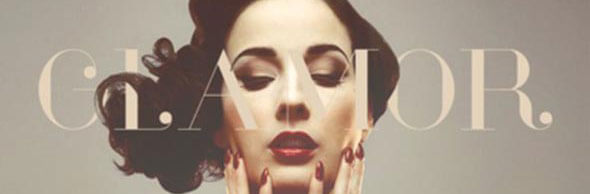
ダウンロード可能な25の大文字フォント
昨今、デジタル世界では字体やデザイン、また、どのように見られるかといったことが注目されています。もし、あなたがウェブデザイナーや電子広告代理店なら、プロジェクトのために、きちんとしたフォントを使うことが重要になります。なぜなら、フォントにはあなたのデザインを目立たせたり、訪問者や顧客を引きつけたりする力があるからです。
字体や書体が仕事の出来に大きな影響を与えることは疑いの余地がありません。デザイナーは、何かを制作する際には、字体のもつさまざまな法則に注意を払う必要があります。たとえば、書体を使う際に重要な法則のひとつは、ウェブサイトで互換性のある2種類のフォントが使用できるということです。3つや4つの書体を超えると、内容から離れ始め、読者が混乱することになり、結果的にサイトから立ち去ってしまうことになってしまいます。
そこで、あなたの仕事をより効率よくするために、ウェブですべて無料でダウンロードできる大文字フォントを探すことにしました。このようにして、あなたを手助けし、応援することのできる25の無料大文字フォントを集めました。これらの素晴らしい大文字フォントのほとんどは、個人用にも商用にも無料でご利用いただけます。私たちとともに、気軽に字体を共有しましょう。
Intro Condensed
この豪華なセットは50の個性的なフォントと太字から作られています。あらゆるサイズの見出しに適しており、どんなタイプの背景にも合います。Tシャツやポスター、ロゴに最適です。掲載元のサイトをご覧になれば、このフォントが洗練されたグラフィックデザインのなかで、どのように使用されているのかといった様々な例をみることができます。
Rex
Rexは3つの太字(light、bold、bold inline)が選択可能なフォントです。すべて大文字のこちらのフォントは、あらゆる種類の背景や、Tシャツ・ポスター・ロゴへのアイデアに適しています。すべて大文字のフォントですが、大文字と小さい大文字の間に違いが見られます。この小さなこだわりが、あなたのプロジェクトに大きく貢献することでしょう。
La Mana
La Mañaはxハイトと、それに適した横幅が特徴のスラブセリフです。美しい先端や素晴らしいマチがあり、見出しや広告に最適です。特別な注意を払って作られており、2種類の太さ(regularとrelief)と175種類のオープンタイプの合字、1000組以上のタイトカーニングはご自身のフォントライブラリを、手動で素晴らしいものへと変えてくれることでしょう。
Uni Sans
Uni SansはFontfabricから提供されています。4種類の大文字の太さが使用されており、無料でダウンロードすることができます。掲載元のリンクでは、どのようにこのフォントを使用するかご覧になることができます。
Langdon
LangdonはXLN Telecomの新しい書体です。しっかりとした力強い書体は、個人用および商用どちらでも利用可能です。イギリスのスティーブン・ボナーとグラフィックデザイナー、イラストレイター、タイポグラファーが共同して作成しました。
Baron
こちらの大文字表記は古典的なサンセリフフォントファミリーをもとに作成されました。ポスターならびに見出しへの使用が理想的です。ユニークな外観はとても目立ちますので、デジタル媒体と印刷媒体の両方へのご利用を強くおすすめします。
Hipstelvetica
Hipstelveticaは有名なヘルベチカデザインに影響を受けて作成されました。こちらの斬新なフォントは個人および商用、どちらも完全に無料です。力強く幾何学的な見た目は、見出しにおすすめです。
Bebas Neue
Bebas Neueは新しく4つの要素(thin、light、book、Regular)を取り込んだ優雅なサンセリフ書体です。こちらの書体はウェブ、印刷、アート、あるいは商用にも適しています。面白いことに、今ではこのフォントは「ヘルベチカの無料のフォント」として知られています。
Code
Codeは先進的で高級な書体です。あらゆる種類のグラフィックデザイナー、その他ポスター、ロゴ、バナーといったアイテムに利用できるでしょう。このフォントはとても多様で、多くの言語でご利用いただけるうえに、MacとPCのどちらにも互換性があります。
Komoda
Komodaは見出しや論評、ポスターデザインに適したサンセリフ書体です。この書体は個人利用及び商用利用どちらも無料です。転載元のリンクでは、このフォントのすべての字体を見ることのできる動画が視聴できます。
Fancy Me
Fancy Meフォントは現代的で論評に最適です。こちらの書体も個人利用、商用利用ともに無料です。とても素晴らしいフォントなので、ダウンロードした後にさらにご利用いただくために、ご自身のフォント目録に追加することをお勧めします。
Canter
Canterはタイトルやポスター、見出しへの表示のために作成された、すべて大文字のフォントです。特に優れた書体は6種類の太文字にあります。アメリカのニューヨークに拠点をおくクリストファー・J・リーによって作成されました。
Moderne Sans – Free Typeface
Moderne Sansはマリウス・ケンプケンによって、1920年代のフォントを参考に作成された書体です。手紙や法律文書、数字、そしていくつかの代替文字に利用できます。デジタルにも印刷デザインにも利用できるうえに、個人利用、商用利用、どちらも使用可能です。
Smaq Typeface
Smaqは8つの無料のスタイルを持つ装飾された書体です。このフォントはポスター、ロゴ、見出しなどに最適です。ラテン文字とギリシャ文字の大文字があります。私たちはこの太くユニークなフォントを色鮮やかに使用することで、よく目立たせ、作品に一流の風格を与えます。
Mohave
大きいサイズ用にデザインされました。3つの太字(regular、semi-bold、italics)があります。見出しやポスター、タイトルなどの表示におすすめです。このフォントはデザイナーのガンピータ・ラハーユによって作成され、とても多目的であるにもかかわらず、無料でダウンロードできるうえに、将来のプロジェクトで使用するためのデザイン目録に追加することができます。
ADAM.CG PRO – Free Typeface
このサンセリフ書体はFutura. ADAM.CGに影響を受けており、洗練されたなめらかな書体は、見出し、ポスター、字幕に適しています。ADAM.CGはアップデートされており、今では新しい字形と2,000以上のカーニングが用意されています。
SIMPLIFICA Typeface Free
SIMPLIFICAはシンプルで現代的なサンセリフ書体です。このフォントは慎重にデザインされており、簡潔で快適なリーディングをご提供します。簡潔で均一な外見は、ウェブデザインやプレゼンテーションに最適ですので、あなたのアイデアが他のものから、より目立つようになります。
OSTRICH SANS INLINE
Ostrich sans inlineはOstrich sans roundの新しいバージョンです。より洗練されただけでなく、完全無料です。タイトルやポスター見出しにおすすめですが、過剰な複雑さを回避するために、少しシンプルなフォントと合あわせるのがいいでしょう。
PRIMUS
Primusは丸いエッジをおびた幾何学的な書体です。よりよい見栄えを目指しました。こちらの書体は、ロゴタイプ、ブランドアイデンティティーや広告などの表示におすすめです。テキストとしてご利用になられる場合、Primusは簡潔で楽しいリーディングをご提供します。ですのでぜひ、ダウンロードされることをおすすめ致します。
Chawp
Chawp表示はいくつかの言語に対応しています。無料ダウンロードバージョンには、OTFやTTF、ウェブフォントファイルが含まれています。Chawpは黒板の板書きを参考に作成されています。ウェブデザインやその他グラフィックデザインなどに最適です。
Multicolore
Multicoloreは丸みを帯びたカラフルな無料フォントです。こちらを使用することで、見出しやポスターなどへのテキストを簡単に作成できます.OTFファイル、EPSファイル、aiファイルのフォントフォーマットから作られています。抽象芸術を作成したいのであれば、少々の文字を積み重ねることで作成することができます。
Manteka
Mantekaは見出しやポスターなどの文章へ理想的なフォントです。個人利用が無料なだけでなく商用にも利用可能です。丸みを帯びた字があり、力強く鮮やかなポスターを作成する際に、私たちが使用するお気に入りのひとつです。
Unveil
Unveilは様々な申込書に理想的なフォントです。ポスター、招待状、雑誌の見開き、さらにロゴやTシャツにも使用できます。Vector書体は異なる5つのスタイルで利用できます。Unveilは無料でダウンロードできますので、今後のプロジェクトにご利用いただけます。
Portica Regular Typeface
PORTICA™はヘルベチカに習った簡潔なサンセリフ書体です。この新しい書体は、表現豊かなタイポグラフィーに最適です。独特の幾何学的表現はポスターデザインやウェブデザインに適しています。
Glamor – Chic & Modern Free Type Family
Glamorタイプファミリーには、24のフォントと、フォントごとの200を超えるユニークな文字があります。こちらも個人利用および商用利用無料です。OTFファイルとTTFファイルのzipファイルが用意されています。